大家的第一堂字體通識課
justfont 設計的第一份字體教案
( 適用小學高年級以上 )
為什麼需要字體教育?
如果有一天,文字消失了,我們的生活會有什麼改變?我們以文字記錄、傳達、交流,充斥在生活中的文字是我們不經意會忽略的風景,而這片安靜的風景,其實是國人美感力的展現。
justfont 長期以「更好的文字風景」為旨,推廣字體知識。我們期待與國人一同學習欣賞文字造型,改善字型應用技能,增進生活中的美感經驗。從長期的推廣經驗中,我們了解到,若要達成願景,基礎教育不可或缺,因此開啟了「字體教育普及計畫」。我們期待藉此深耕校園,帶領孩子們從小認識字體,在成長過程中,逐步由學習欣賞文字,到懂得使用字體,最終將所習得的美感鑑賞力與字體應用力,轉化為增添生活美學的原動力。
「字體教育普及計畫」以打造涵蓋全年齡的完整學習教材為目標,進行知識內容的編寫。率先推出字體基礎知識與欣賞辨別的教材,免費公開,歡迎老師們自由下載運用!
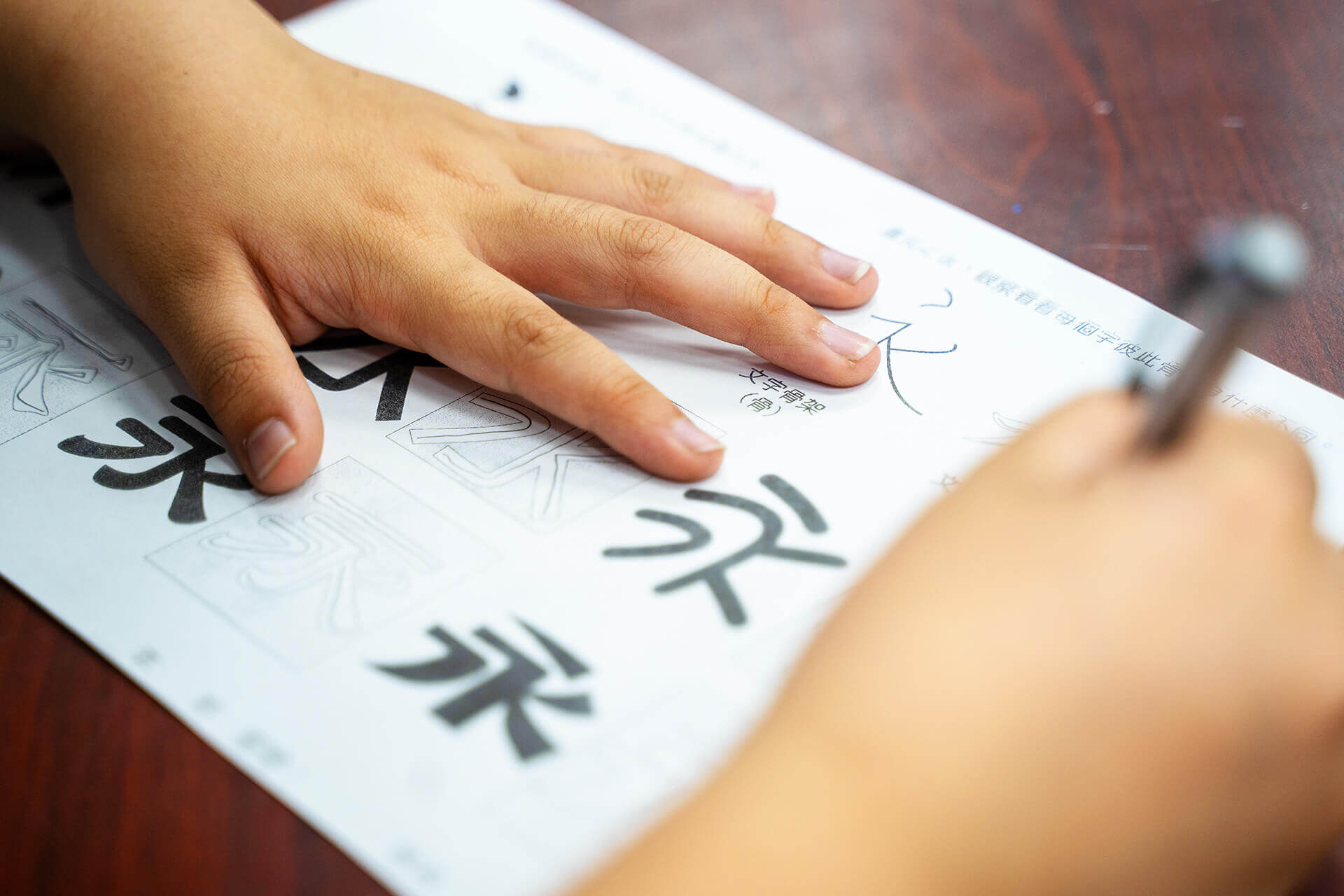
從生活開始
教室佈置、學校作業、求職履歷,乃至於公告、包裝、字幕,字體如何影響我們的生活?為什麼有些字感覺很緊張,有些文字看了就流口水,有些文字是大嗓門,有些文字不太起眼卻很常見?讓我們從生活周遭的文字開始,熟悉字體的表現方式。
這份教材的實驗與推廣
從 2020 年初開始,我們將小學生適用的字體課雛形引進部分學校,經過反覆的實驗與討論,完成了「大家的第一堂字體通識課」。目前全台有逾 300 位中小學生,體驗過本份教材。
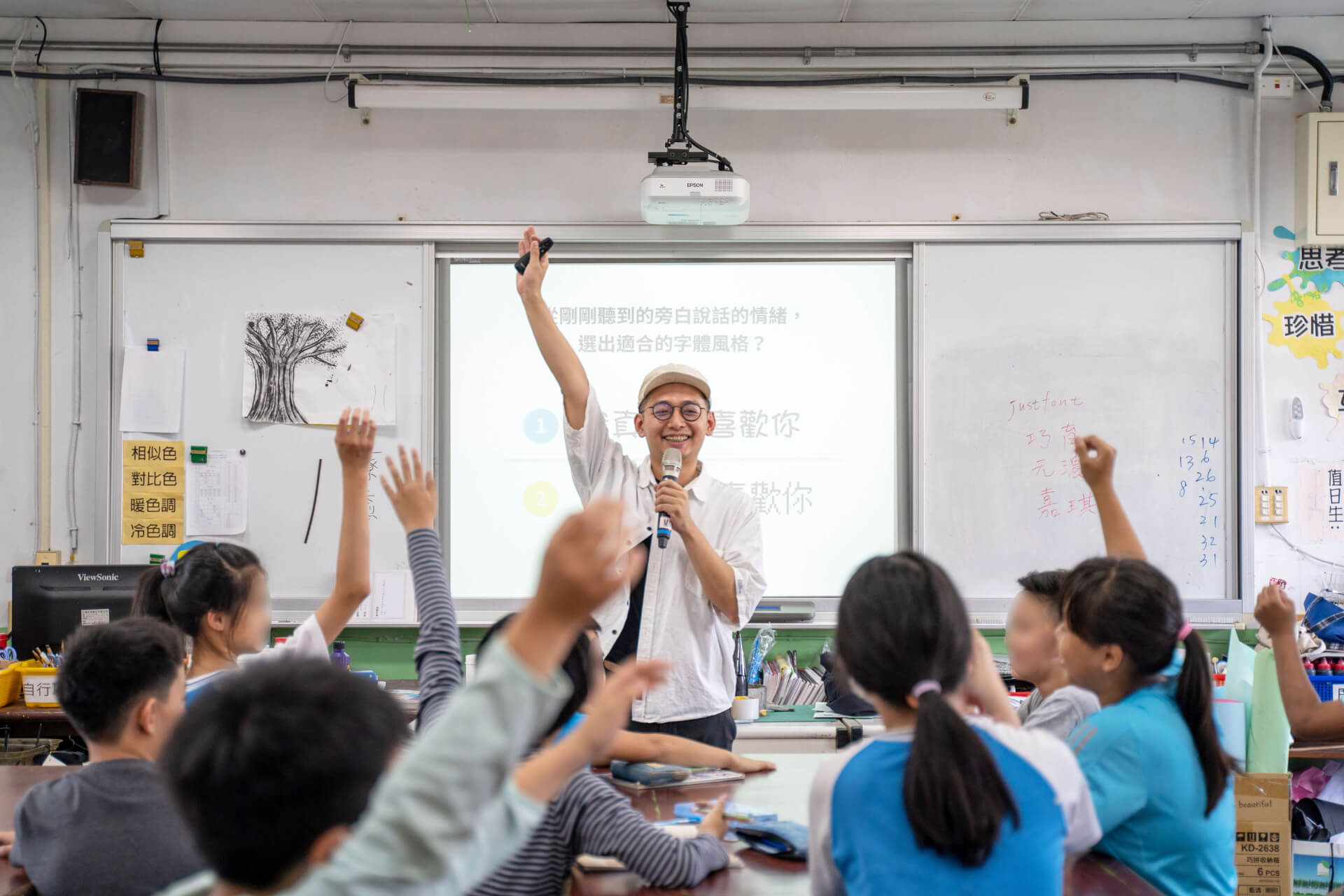
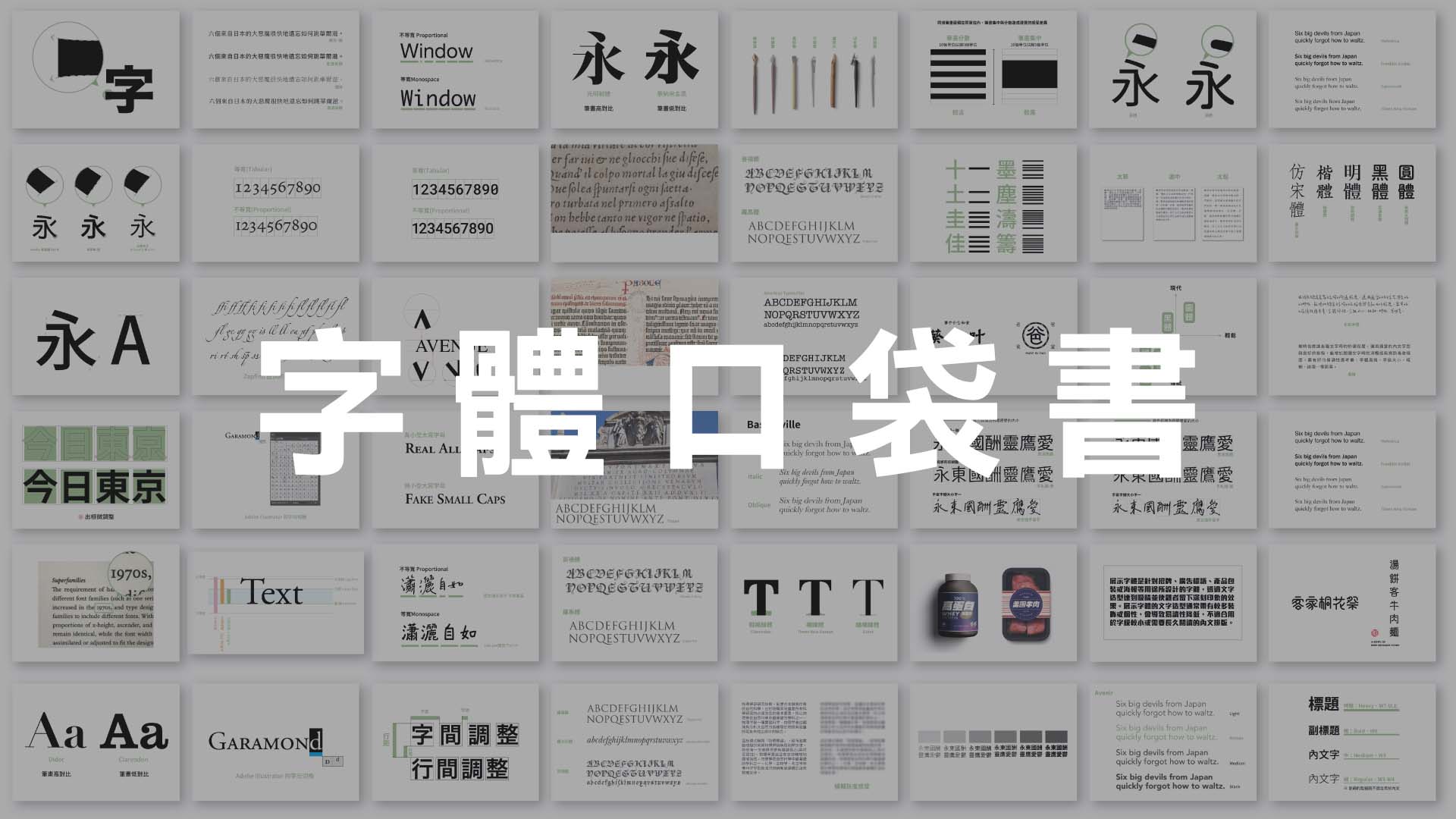
輔助資源:字體口袋書
同步推出「字體口袋書」,收錄 61 條字體學習相關的基礎字詞,配有圖例與延伸閱讀,簡潔易懂。收錄詞條包含:漢字概念與常見風格、歐文結構與常見風格、排版應用常用字詞等。除補足知識脈絡以輔助教學外,更可以引導學生進入下一步的進階知識與賞析應用。
教材內容包含
本項教材為 4 週,8 堂課的基礎課程,適用的年齡層為小學五、六年級以上。課程包含基礎字體知識、基礎應用概念,以及兩項課堂成果。教材免費下載,也希望您與我們分享課堂使用的成果!(詳見教材說明書)
學生可以習得
● 增加生活中的洞察力與美感經驗
● 體會漢字之美
● 學會分辨不同場合適用的字型
● 在生活中應用字型知識
| 週數 | 課堂與內容 | |
|---|---|---|
| 第一週 | 文字的表情 | 認識基本字體、感受文字的情緒 |
| 第二週 | 文字的功能與情境 | 了解字體風格、資訊傳達功能、情境應用 |
| 第三週 | 繪製生活中的標語 | 透過文字骨架來製作校園活動的標語 |
| 第四週 | 創作自己的名字 | 透過複合媒材完成文字的拼貼創作 |